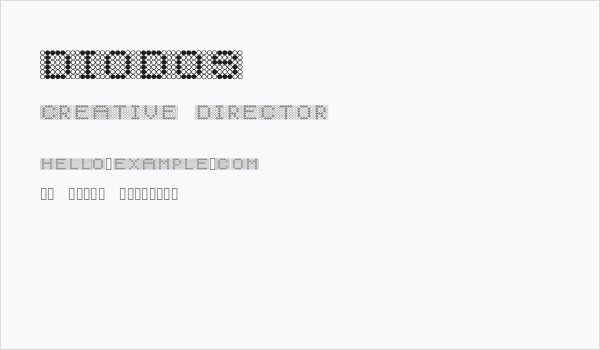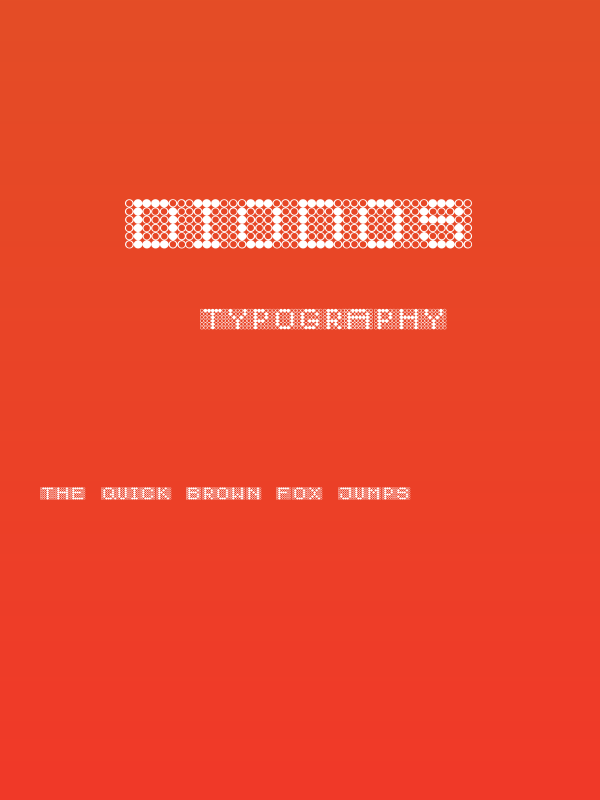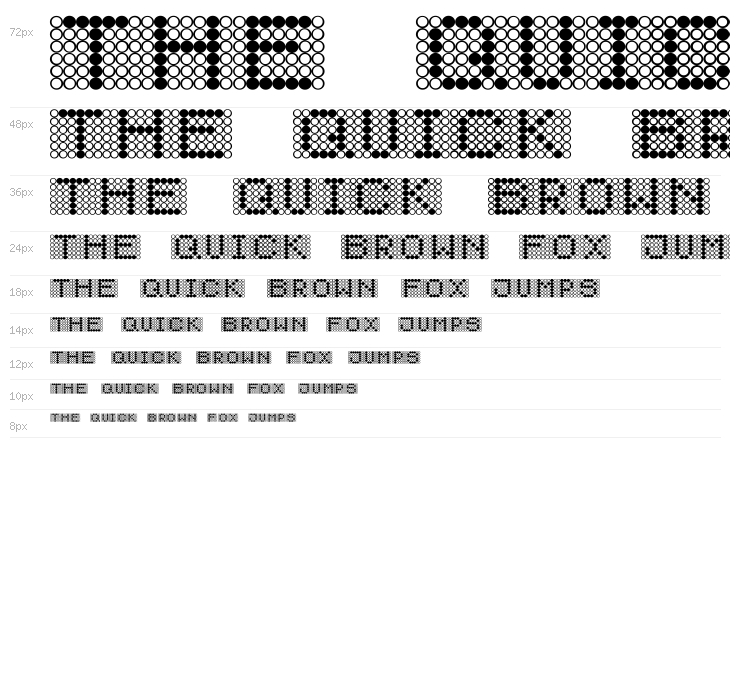
Diodos Font
| Nome | Diodos |
| Caso d'uso | Logos, Headlines, Digital Displays |
| Progetti proposti | Ideal for tech-related branding, digital art projects, futuristic-themed posters, and innovative product packaging. |